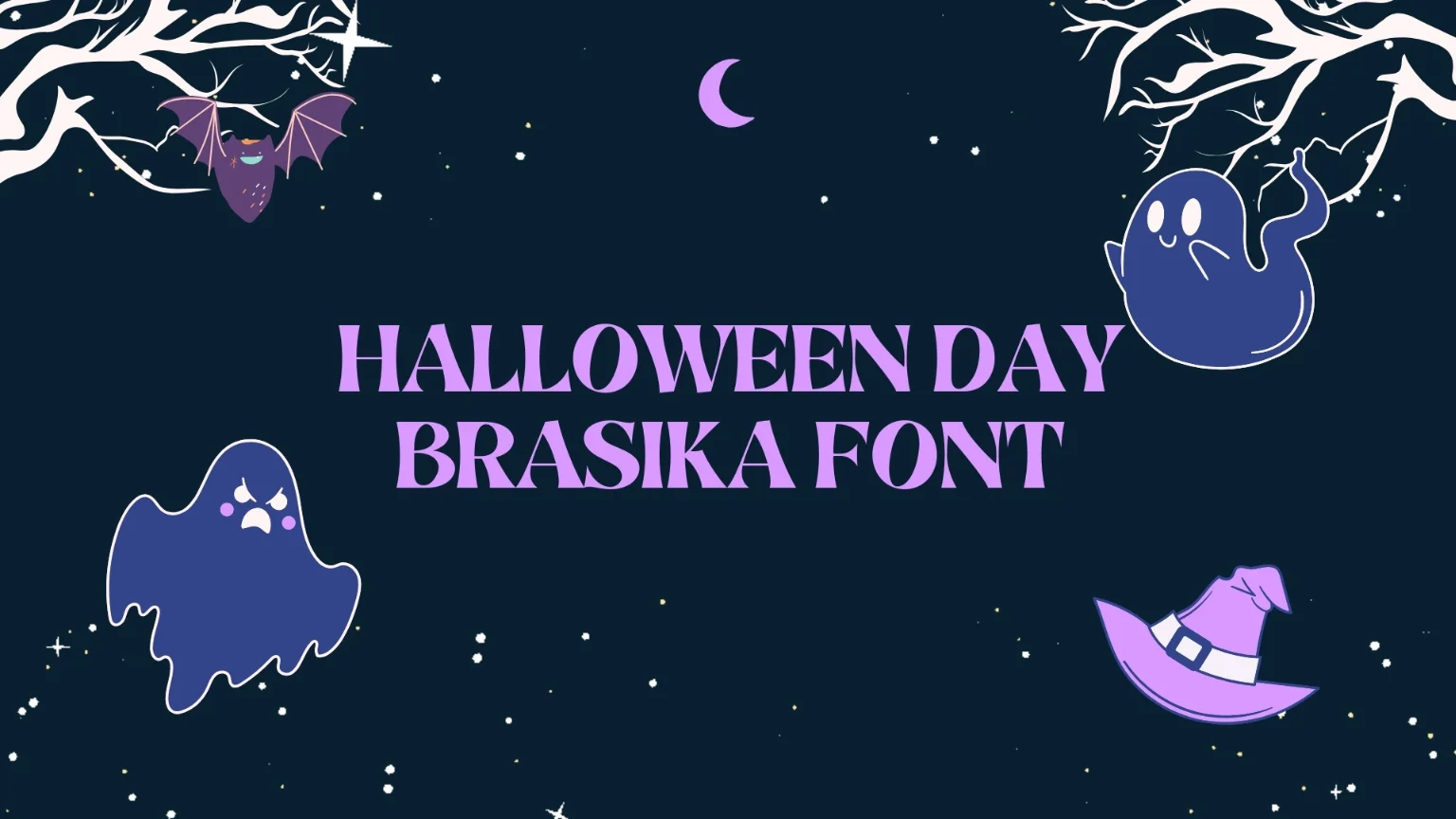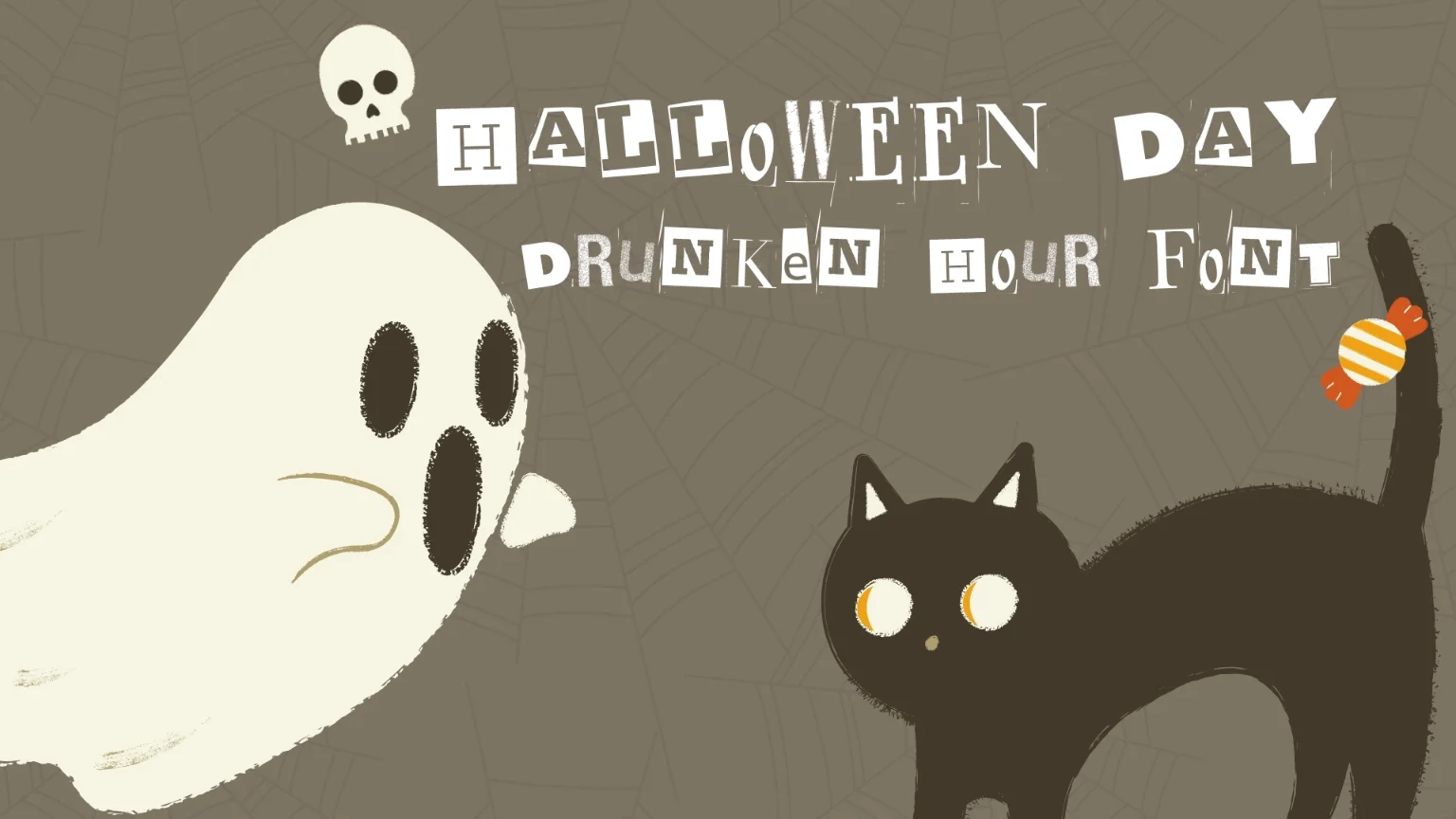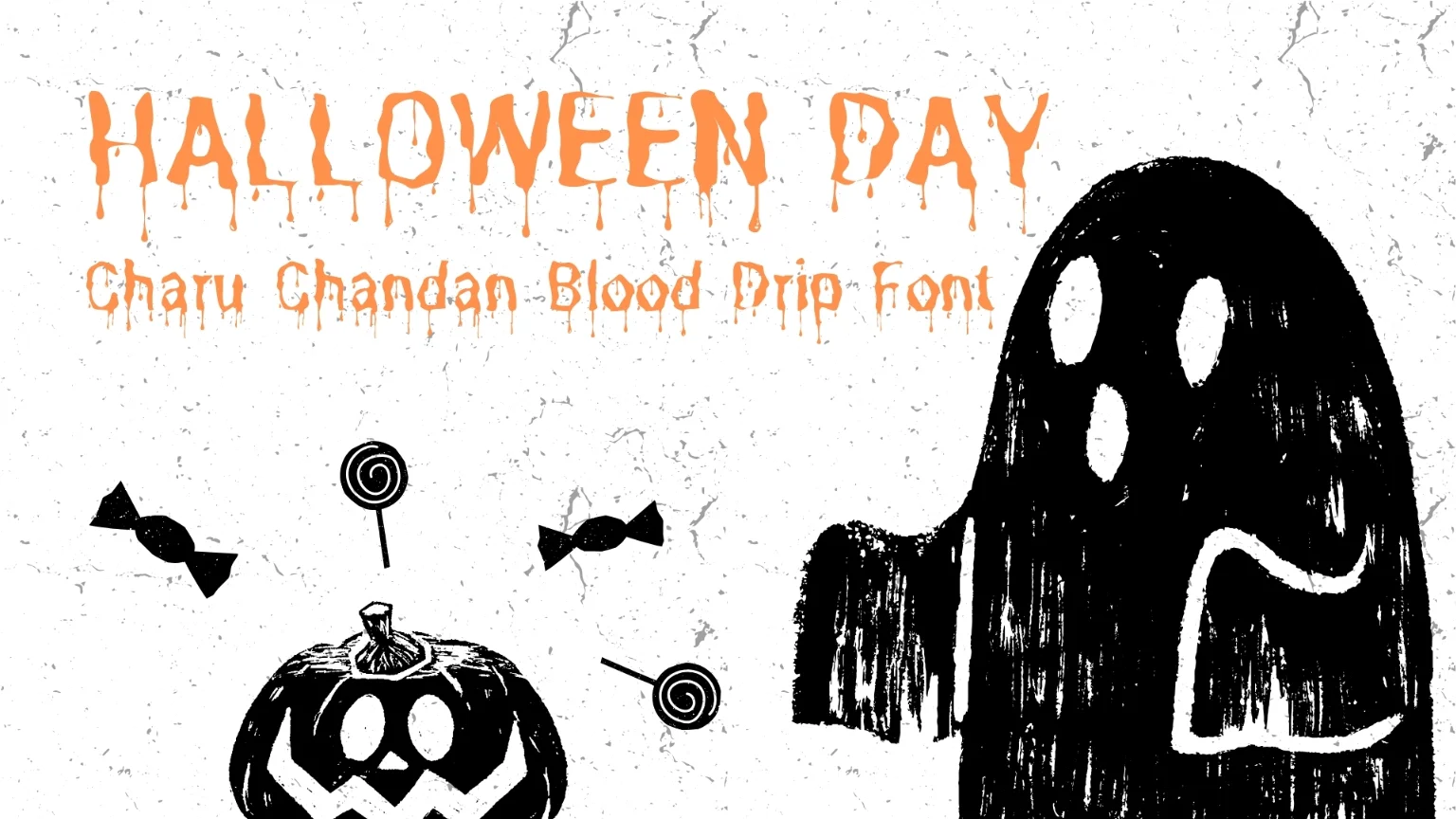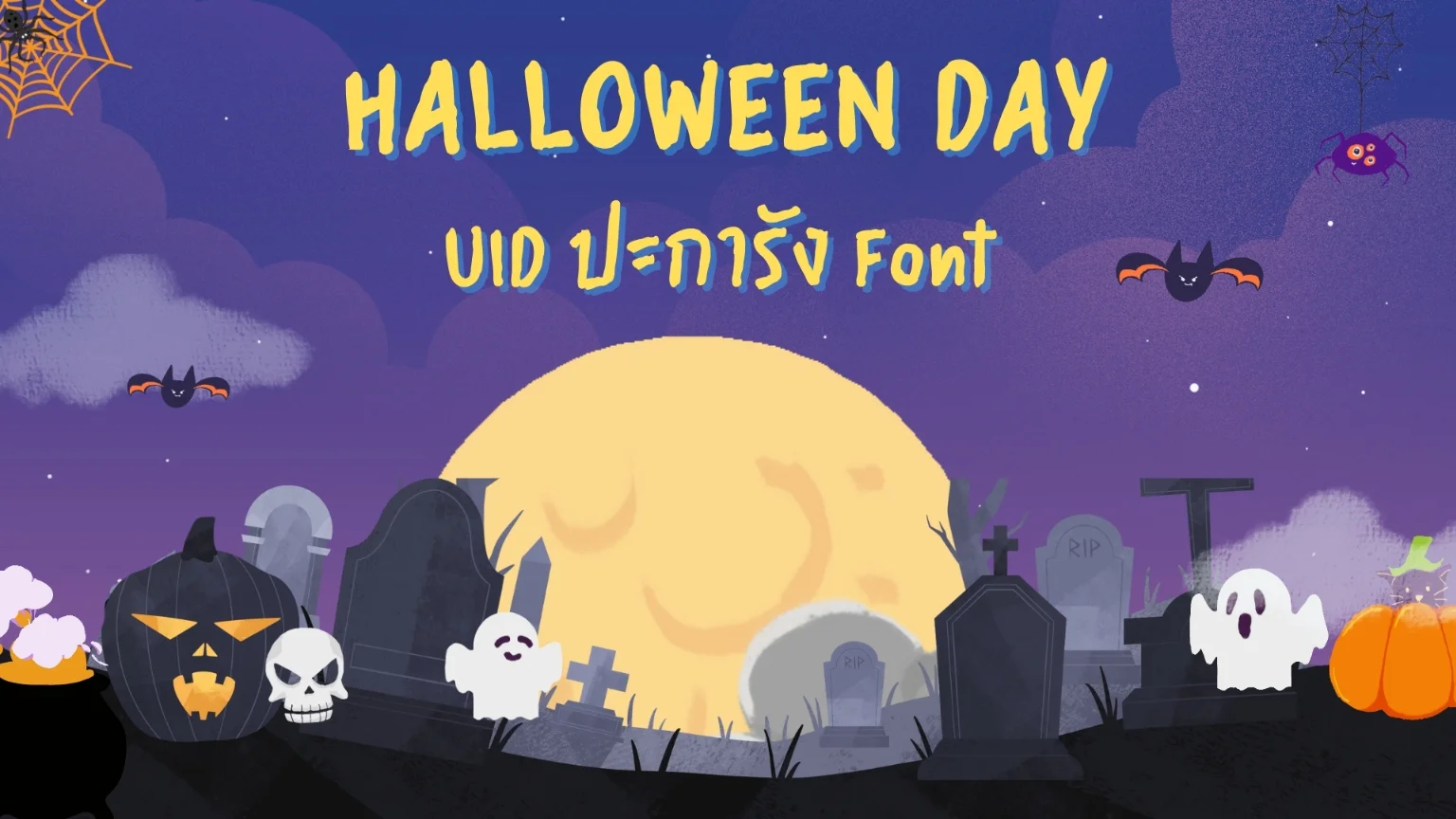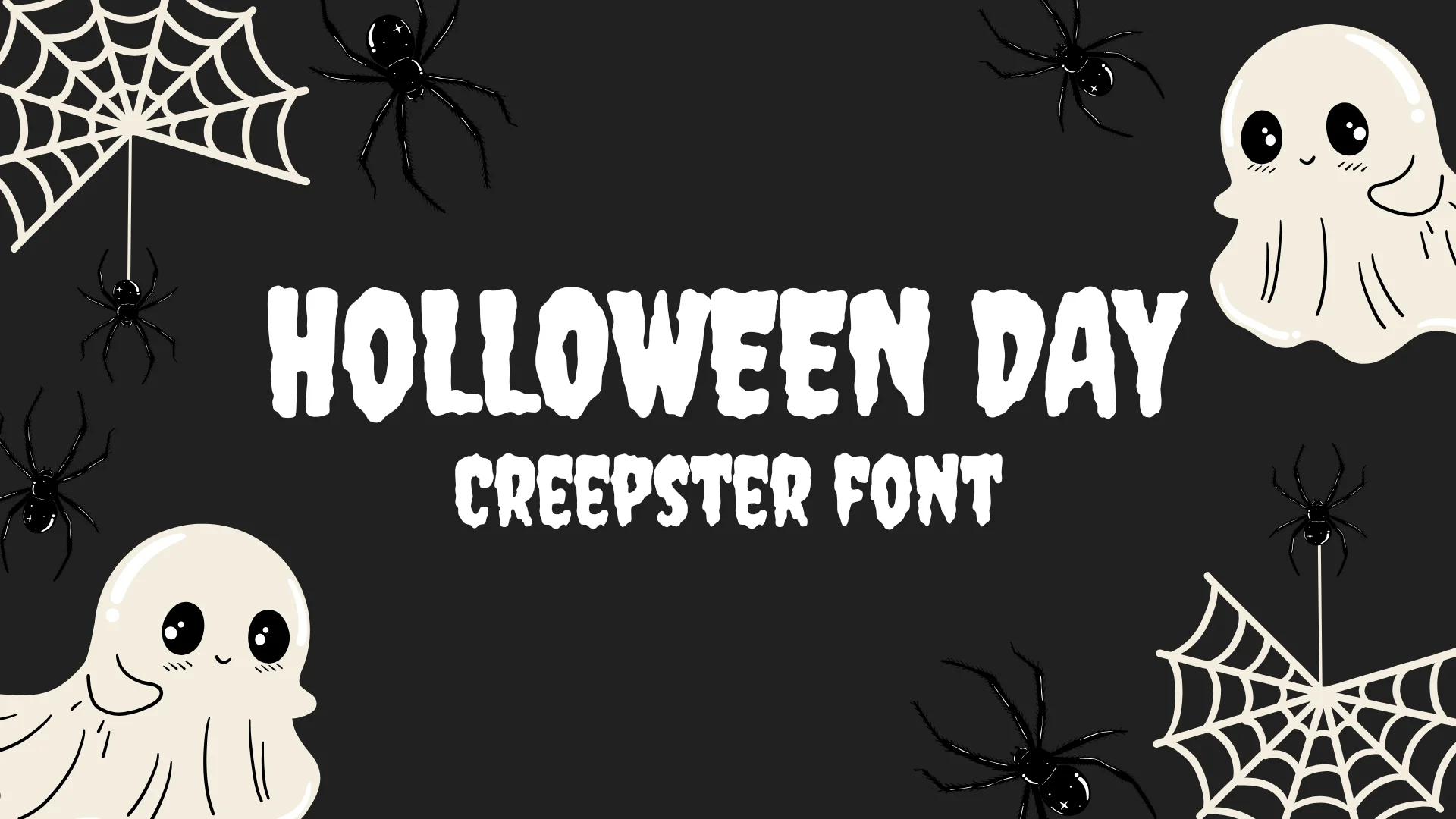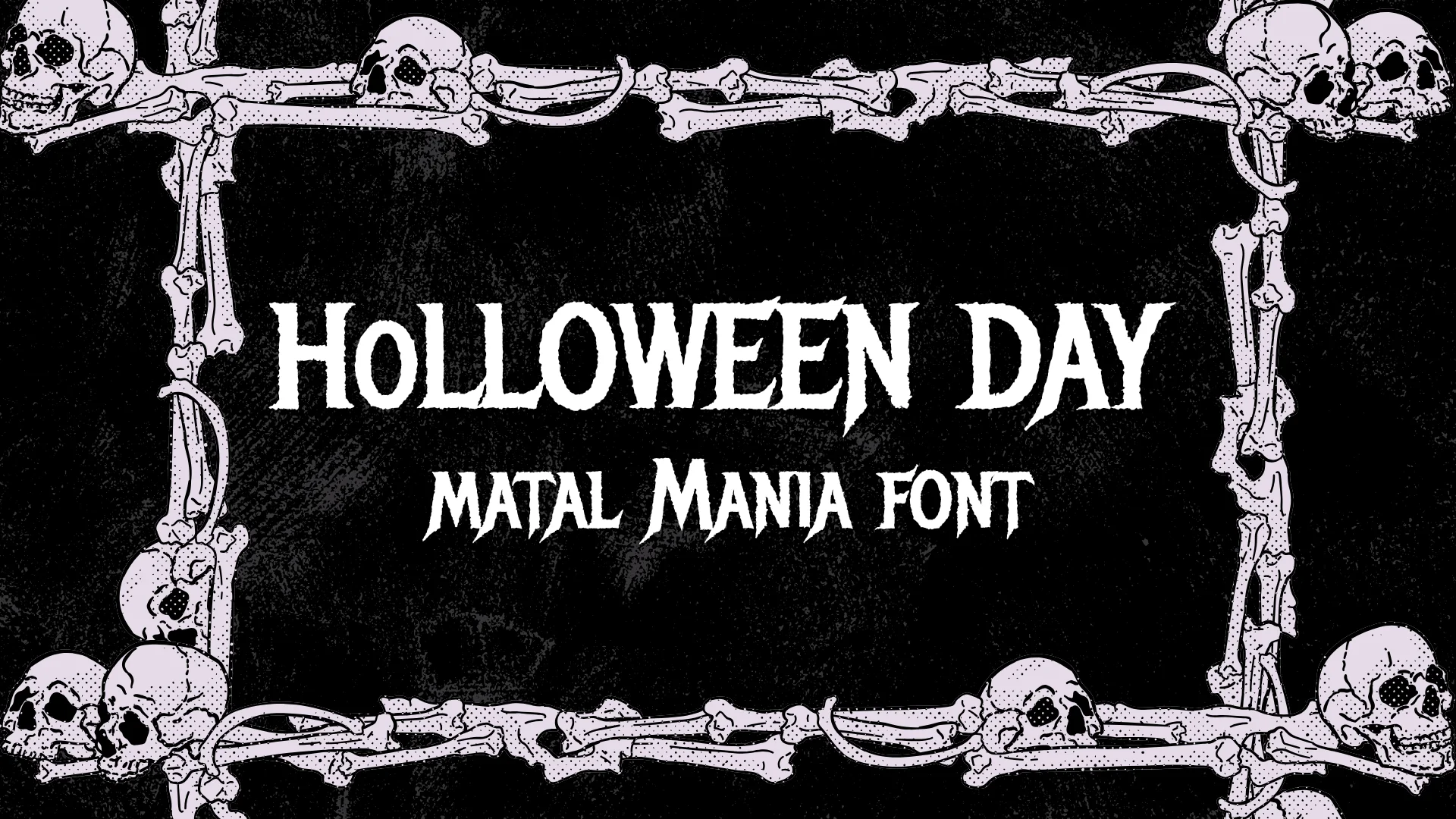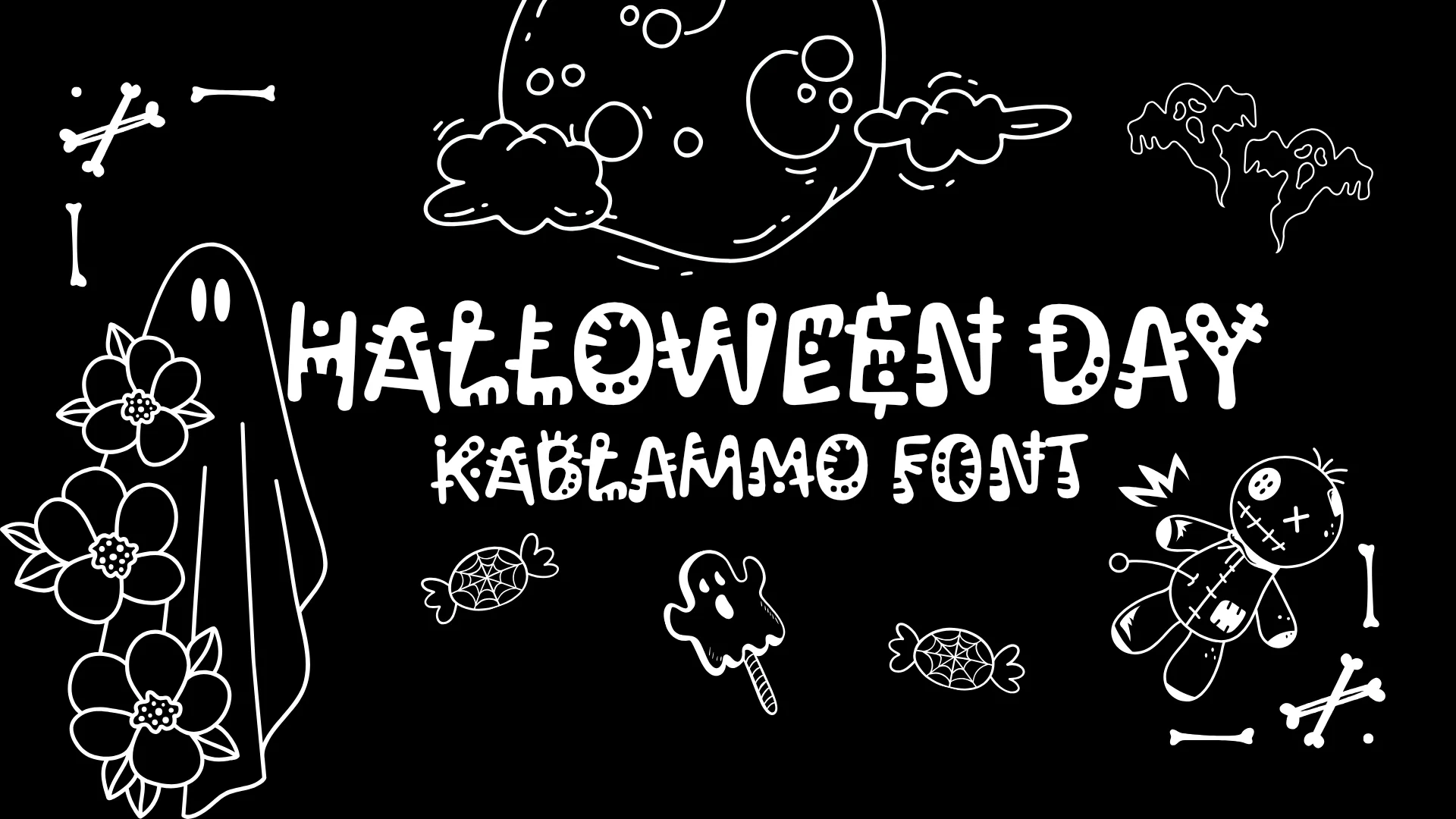
แนะนำ 7 ฟอนต์สไตล์ Halloween ใช้ทำพรีเซ้นต์น่ารัก ๆ ฟรี
สำหรับใครที่สำหรับหาฟอนต์น่ารัก ๆ ในช่วง Halloween วันนี้เราจะมาเเนะนำ 7 ฟอนต์สไตล์ Halloween จะมีแบบไหนกันบ้าง มาดูกัน !
แนะนำ 7 ฟอนต์สไตล์ Halloween ใช้ทำพรีเซ้นต์น่ารัก ๆ กัน
สำหรับใครที่สำหรับหาฟอนต์น่ารัก ๆ สไตล์ Halloween ไปทำพรีเซ้นต์ หรืองานต่าง ๆ วันนี้เราได้รวบรวมฟอนต์จากหลาย ๆ ที่มาแนะนำกัน
1. UID ปะการัง Font – Canva
2. Charu Chandan Blood Drip Font – Canva
3. Drunken Hour Font – Canva
4. Brasika Font – Canva
5. Creepster Font – Google Fonts
6. Metal Mania Font – Google Fonts
7. Kablammo – Google Fonts